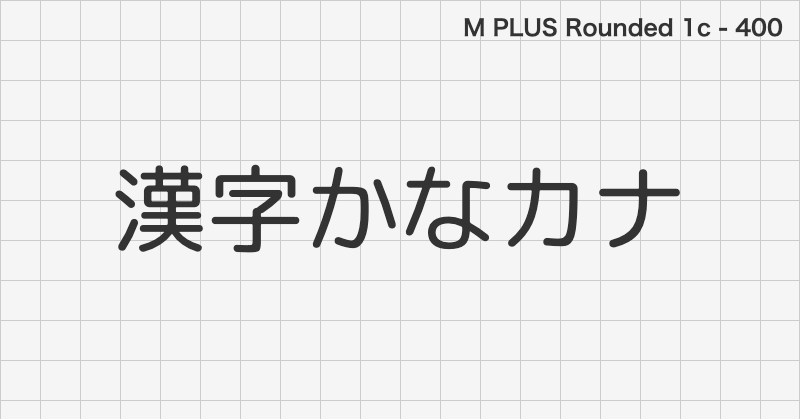
M PLUS Rounded 1c は、丸みを帯びたデザインのゴシック体フォントで、親しみやすさと柔らかさが特徴です。さまざまなウェイトを持ち、多様な用途に対応しています。
日本語ラテン文字ラテン文字拡張ベトナム語キリル文字ギリシャ文字ギリシャ文字拡張ヘブライ語キリル文字拡張 に対応しており、多言語環境でも統一したデザインで表示できます。
ウェイトは 細字標準太字 を収録しており、注釈から本文、見出し、引用文とあらゆるケースで使えます。
M PLUS Rounded 1c は、M+ Fonts プロジェクトによって開発され、さまざまなデザインスタイルに適合することを目指しています。特に、丸みを帯びた形状が印象的で、親しみやすい印象を与えます。
作者名 Coji Morishita, M+ Fonts Project